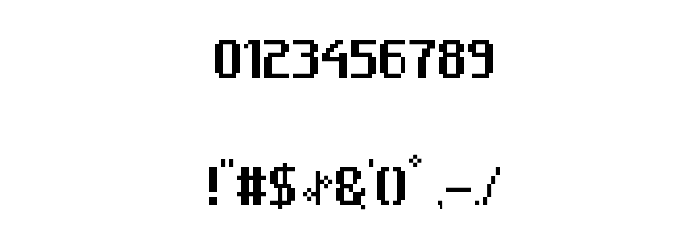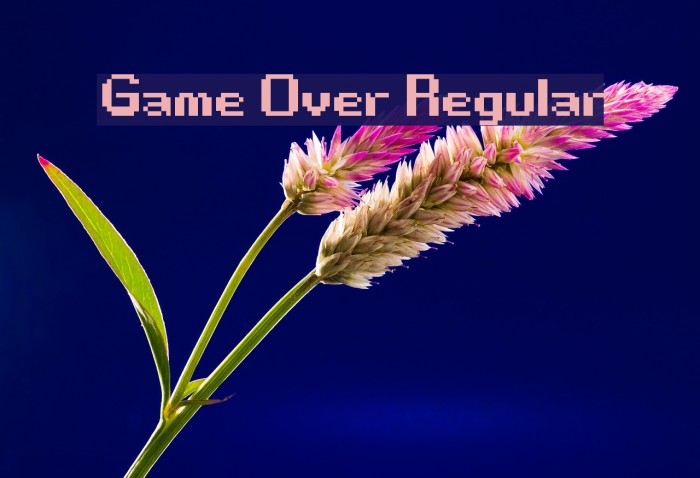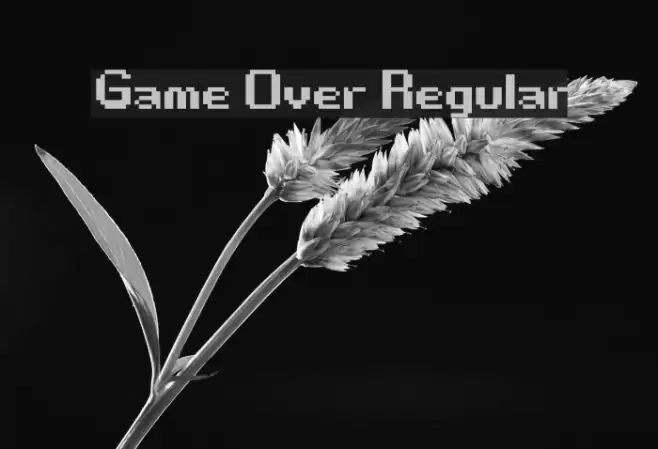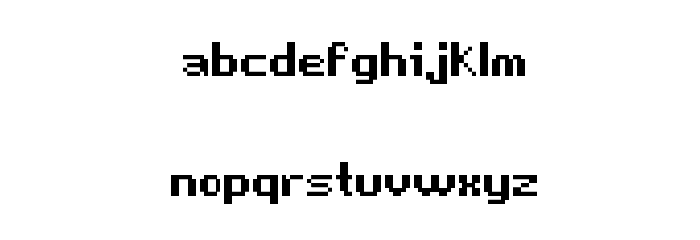
Game Over Regular Font
Font by Pedro Munoz Pastor - fodkito.deviantart.com
| Caso d'uso | Logos, Headlines, Digital Art |
| Progetti proposti | Ideal for video game designs, retro-themed posters, digital art projects, and any creative work that seeks to capture the essence of classic gaming. |